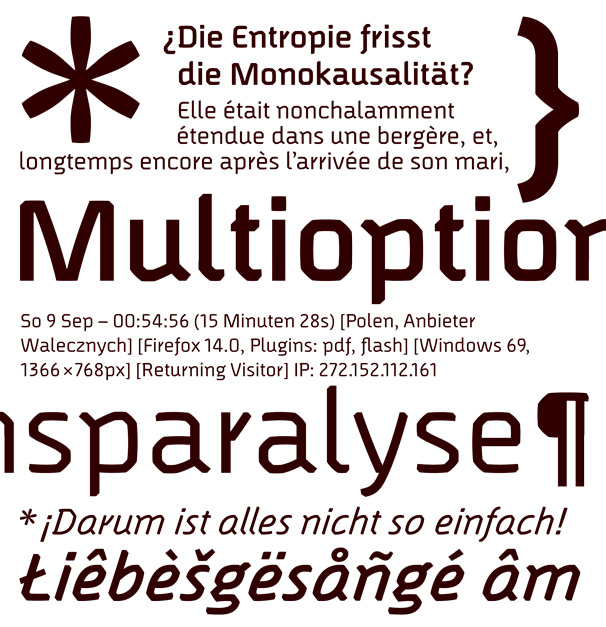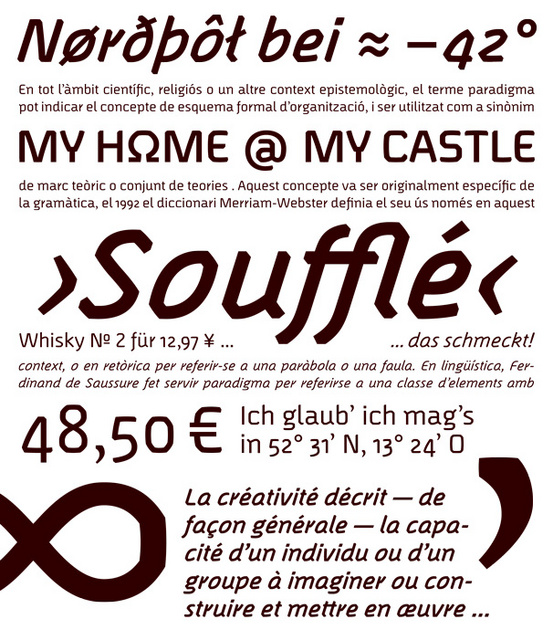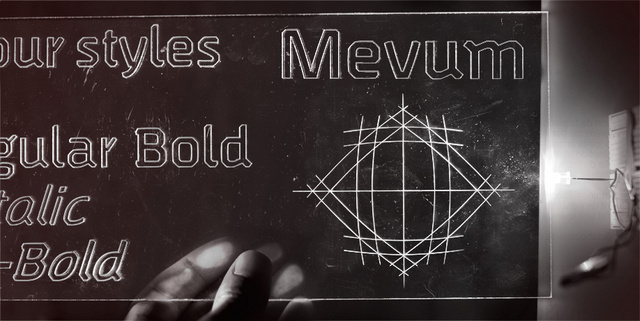
Neue Schriftfamilie: »Mevum«
die »Mevum« wurde vor einem Jahr auf 26+ Zeichen – einer Plattform für studentische Schriftenentwürfe – vorgestellt. Nun ist aus ihr ein ganze Familie geworden mit einer ungewöhnlich schrägen Italic und dazugehörigen Bold-Schnitten.
Konzept
Der Grundidee eine Schrift zu zeichnen, die konstruiert und gleichzeitig eine warme und freundliche Anmutung besitzt, hat mich vom Entwurf bis zur Realisierung begleitet. Eine simple, rechteckige Form mit abgeschrägten Ecken und einer subtilen Wölbung nach außen bildete das Grundkonzept. Damit soll die Mevum einen Bogen zwischen Mensch und Technik schlagen, ohne dabei allzu verkopft daherzukommen. Die Formensprache der Mevum greift somit Wesenzüge aus z.B. Architektur, Maschinenbau, Elektronik und Wissensschaft auf, die sich einerseits durch eine gewissen Sachlichkeit und andererseits durch einer Orientierung am Menschen auszeichnen.
Besonderheiten
Trotz der reduzierten Formensprache unterscheiden sich bei der Mevum ähnlich aufgebaute Zeichen deutlich voneinander. Das kleine l unterscheidet sich vom kleinen I durch seinen Abschluss. Auch das einstöckige a und zweistöckige g sind für eine bessere Lesbarkeit nicht unrelevant. Außerdem sollte die Buchstabenkombination aus rn in kleinen Schriftgrößen nicht zu einem m »zusammenlaufen«. Für eine typische Serifenlose ungewöhnlich ist auch das Minuskel f, das mit seiner Unterlänge auch den Durchschuss der darauffolgenden Zeile ein wenig belebt.
Neben der deutlichen Differenzierbarkeit der Zeichen zueinander, habe ich mich auf die Beziehung zwischen Regular und Italic konzentriert. Im Gegensatz zu einer gewöhnlichen Serifenlosen hat die Italic der Mevum eine starke Neigung von 18°. Dadurch kann die Italic gegenüber der Regular einen noch ausgeprägteren Rhythmus und Charakter entwickeln.
Subtile Details, wie die kleinen abgeschnittenen Ecken oder bspw. die leichte Rundung am horizontalen Balken beim T oder die gekürzten Serifen bei B, D, R und P bleiben in kleinen Schriftgrößen dem Betrachter zuerst verborgen und treten erst in höheren Schriftgraden in Erscheinung.
ja, sieht interessant aus und gefällt mir eigentlich recht gut.
@ R::bert: Darf ich erfahren, was Deine Augen dort sehen?
Ich schätze, Kollege Robert erfreut sich an der Tatsache, dass es mit der Mevum nun eine weitere Schrift gibt, die uns mit einem Versaleszett beglückt. :-D
So ist es :huhu:
Man könnte den Eindruck gewinnen, dass Gestalten Fonts als Foundry bzw. Schrifthändler dem Versaleszett (auch) sehr offen gegenüber steht. Oder ist das Vorhandensein eines solchen immer nur ausschließlich dem Willen des Schriftgestalters zu verdanken?
Gibt es da diesbezüglich gewisse »Richtlinien«, die bei Zusammenarbeit gelten?
@ Robert: Also in dem Fall habe ich mir das Versal-Eszett selbst zum Thema gemacht. Von Seiten der Gestalten Fonts gab es hierzu keine Vorgaben. Die zusätzlichen Ziffernvarianten für z.B. Versal- und Tabellensatz wollte ich auf jeden Fall berücksichtigen und wurden natürlich auch von Gestalten Fonts begrüßt.
Ich hatte ja selbst die Diskussionen über das Versal-Eszett – auch hier im Forum – teilweise verfolgt und bin letztendlich (Bei der Fragestellung, ob man es nun benötigt oder nicht.) dann doch zu dem Entschluss gekommen, ein Versal-Eszett zu zeichnen. Habe mir gedacht so kann der Anwender selbst entscheiden, ob es zum Einsatz kommt.
@ Robert: Also in dem Fall habe ich mir das Versal-Eszett selbst zum Thema gemacht. Von Seiten der Gestalten Fonts gab es hierzu keine Vorgaben. Die zusätzlichen Ziffernvarianten für z.B. Versal- und Tabellensatz wollte ich auf jeden Fall berücksichtigen und wurden natürlich auch von Gestalten Fonts begrüßt. Ich hatte ja selbst die Diskussionen über das Versal-Eszett – auch hier im Forum – teilweise verfolgt und bin letztendlich (Bei der Fragestellung, ob man es nun benötigt oder nicht.) dann doch zu dem Entschluss gekommen, ein Versal-Eszett zu zeichnen. Habe mir gedacht so kann der Anwender selbst entscheiden, ob es zum Einsatz kommt.